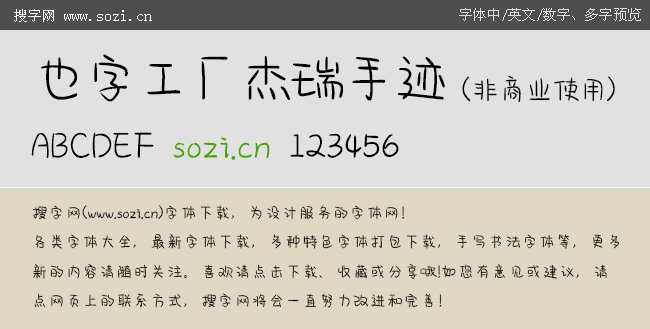
也字工廠杰瑞手跡
搜字網(wǎng)給大家提供一款也字工廠杰瑞手跡(非商業(yè)使用)中文字體下載,也字工廠杰瑞手跡是一款手寫書法字體,字體書寫簡潔流暢,字形端正自然。具有很好的視覺效果。適合應(yīng)用于藝術(shù)設(shè)計、平面宣傳設(shè)計、網(wǎng)頁設(shè)計、海報設(shè)計等應(yīng)用(此字體為個人非商用版,商用可以聯(lián)系:官方網(wǎng)址:https://yefont.com/home,聯(lián)系方式:13798980448)。